Bu yazı tipleri, tasarımlarınızı sonbahar mevsimiyle birlikte gelen olgunluk ve olgunluk duygusuyla dolduracak.
Sonbahar Yazı Tipi nedir?
Sonbahar yazı tipi, Sonbahar mevsiminden ilham alan veya sonbahar mevsiminin simgesi olan herhangi bir yazı tipidir.
Klasik Sonbahar yazı tipleri, rustik, davetkar tipografi kullanır ve sonbaharla ilişkilendirdiğimiz şeylerin görüntülerini çağrıştırır: rahat kazaklar, kavrulmuş kestaneler, balkabağı parçaları, elma şarabı, altın gün doğumları ve zengin hasatlar. Bu yazı tiplerinin tasarımcıları genellikle değişen mevsimlerden ve yaprakların dönüşümünden ilham alır.
Sonbahar yazı tipleri, Cadılar Bayramı, Şükran Günü, Oktoberfest, Şenlik Ateşi Gecesi ve hasat festivalleri gibi yılın bu döneminde gerçekleşen diğer etkinliklerin de simgesi olabilir.
1. Teşekkürler Sonbahar – En İyi Seçimimiz
Teşekkürler Sonbahar, sonbahar mevsimini mükemmel bir şekilde temsil eden sıcak ve samimi bir el yazısı yazı tipidir. Eğlenceli sonbahar temalı tasarımlar için mükemmel olan eğlenceli, tuhaf harf biçimlerine sahiptir.
Neden bizim en iyi seçimimiz
Teşekkürler Sonbahar, Envato Elements'teki en popüler yazı tiplerinden biridir ve nedenini görebiliriz! Sonbaharla ilişkilendirdiğimiz kaygısız iyimserlik duygusunu uyandıran sıcak, havadar, davetkar bir yazı tipi. Aynı zamanda, birçok farklı tasarım türünde işe yarayacak oldukça okunaklı ve çok yönlü bir yazı tipidir.
2. Sonbaharım
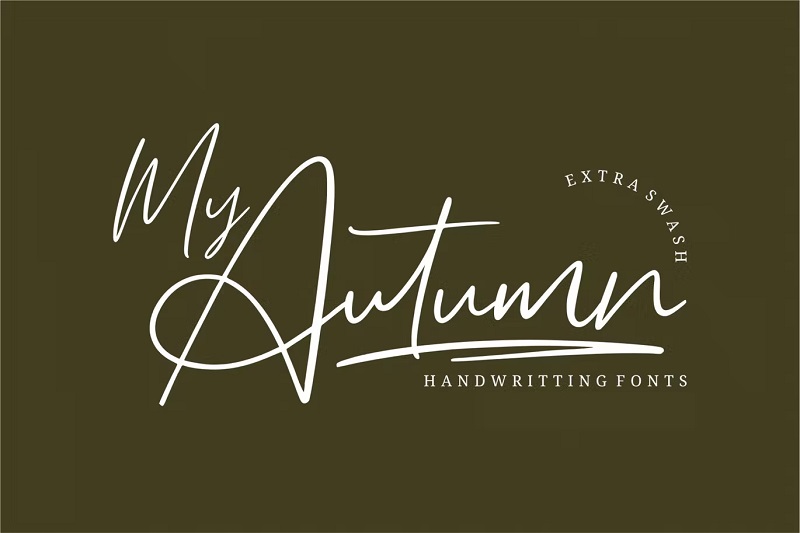
Sonbaharım, Sonbahar temalı güzel bir yazı tipidir. Hassas el yazısı stili çok zarif ve feminen görünüyor ve bunu daha sofistike tasarımlar için harika bir seçim haline getiriyor. Sonbahar etkinliklerinize ve partilerinize davetlerde kullanın. Ayrıca düğün tasarımları, kırtasiye malzemeleri ve marka bilinci oluşturma için mükemmel bir seçimdir.
3. Hasat Ekmeği
Harvest Bread, sonbaharın sıcaklığından ilham alan eğlenceli ve cesur bir yazı tipidir. Posterler, gıda ambalajları ve davetiyeler dahil olmak üzere Şükran Günü temalı tasarımlar için mükemmeldir.
4. Karabira
Birçok insan için Sonbahar, Oktoberfest'in mevsimidir. Bira içmenin, lezzetli yemekler yemenin ve neşeli olmanın tam zamanı. Bu sonbaharda kendi Oktoberfest tarzı bira festivaliniz için bir tasarım üzerinde çalışıyorsanız, Blackbeer sizin için mükemmel bir yazı tipidir. Dört stilde gelen güçlü, gotik bir yazı tipi.
5. Turuncu Yapraklı
Orange Leafy, Sonbahar'dan ilham alan bir başka harika el yazısı ekran yazı tipidir. Sıcak, havadar harf biçimleri, çocuk kitapları, oyuncak ürün ambalajları, Sonbahar temalı oyunlar vb. gibi çocuklara dönük tasarımlar için mükemmeldir.
6. KR Hasat Sonları
KR Harvest Dings, yalnızca dingbat'lardan oluşan bir yazı tipidir. Burada harf veya sayı bulamazsınız; sadece tipografi tasarımlarınızı renklendirmek için süs/dekoratif gliflerden oluşan bir koleksiyon. Tüm dingbatlar hasat mevsiminden ilham alıyor (hacı şapkalarını, akçaağaç yapraklarını, meşe palamutlarını, balkabaklarını vb. düşünün)
7. Sonbahar Keyfi
Autumn Delight, HamzStudio'nun modern, piliç bir yazı tipidir. Tasarımcı aynı anda hem eğlenceli/ilginç ve hem de düzenli/düzenli bir şey yaratmayı başardı. Bu, sabit yükseklikte bir yazı tipidir, bu nedenle tüm karakterler çok düzgün görünür, ancak yuvarlatılmış köşeler ve hafif kıvrımlı çizgiler daha yumuşak bir dokunuş katar.
Sonuç, posterlerden tebrik kartlarına kadar her türlü tasarım projesinde harika görünecek büyüleyici, eğlenceli bir yazı tipidir.
8. Erimiş Canavar
Sonbahar sadece düşen yapraklar ve soğuma sıcaklıklarından ibaret değildir, aynı zamanda Cadılar Bayramı mevsimidir. Bu sonbaharda ürkütücü bir tasarım üzerinde çalışıyorsanız, Melted Monster sizin Cadılar Bayramı yazı tipiniz olabilir.
okunabilirlik
Okunabilirlik hakkında düşünmeyi unutmayın. Kimse okuyamıyorsa, harika görünen bir yazı tipi seçmenin hiçbir faydası yoktur. Büyük boyutlarda kolayca okunabilen yazı tiplerinin daha küçük ekranlarda okunmasının zorlaşabileceğini unutmayın.
Renk
Yazı tipi tasarımı önemlidir, ancak tipografi tasarımlarınızda kullanmayı seçtiğiniz renkler de bir o kadar önemlidir. Sonbahar yazı tipleri, canlı kehribar, kırmızı ve sarı gibi daha sıcak renk paletlerinin yanında en iyi sonucu verir.